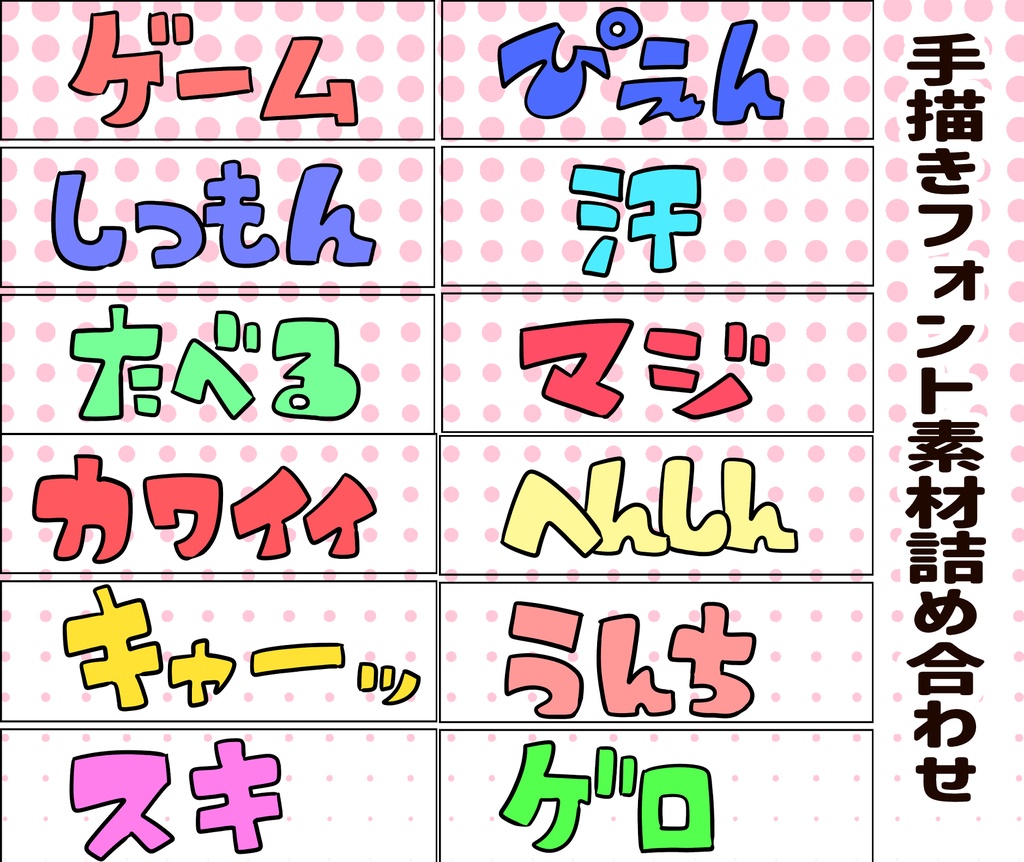
akiramoko手描きフォント・文字素材詰め合わせ・配信や配布物に応援パック(同じ内容です)Digital100 JPYAdd to CartBuy a GiftDownloadDigital0 JPYFree Download6.png (208 KB)Free Download3.png (307 KB)Free Download5.png (236 KB)Free Download1.png (253 KB)Free Download2.png (224 KB)Free Download4.png (270 KB)6.png3.png5.png1.png2.png4.pngAbout Gift柔らかな印象の手描きフォントです。 サムネイルや配布物、動画内素材 こちらは配信者向けのワードが多いかと思います。 様々な用途でお使いになれます。 色変更拡大縮小変形、ご自由にお使いください。 自作発言のみお止めください。 PNGデータ 600dpiakiramokoVisit FANBOX!Stickers騒がしい素直な猫のステッカーakiramoko770 JPYStickers素直な猫のステッカーakiramoko770 JPYT-Shirtsやるなら今しかねぇ猫akiramoko1,750 JPYAcrylic Keychains素直な猫のアクキーakiramoko880 JPYAcrylic Keychains騒がしい素直な猫akiramoko1,060 JPYIllustration (Other)歯科衛生士・イラスト詰め合わせakiramoko100 JPYFonts手描きフォント・文字素材詰め合わせ・配信や配布物にakiramoko100 JPYFonts手書きフォント・文字素材詰め合わせakiramoko100 JPYGlasses & Tumblers & Mugsクロネコマグakiramoko1,750 JPYAcrylic Keychainsクロネコチャンakiramoko880 JPYIllustration (Other)手書き文字・文字素材詰め合わせakiramoko100 JPYFonts手書きフォント・文字素材詰め合わせakiramoko100 JPYMaterials (Other)配信用素材・ビスケットakiramoko100 JPYMaterials (Other)配信素材・手描きフォントakiramoko100 JPYIllustration (Other)スケジュールメモ帳akiramoko0 JPYBackground Images背景画像・星空akiramoko0 JPYMaterials (Other)背景素材集akiramoko100 JPY~Photos【配信画面】写真立て12種・推し色akiramoko100 JPYIllustration (Other)歯科衛生士・歯科助手イラストakiramoko100 JPYGraphics【配信】花瓶・観葉植物セット【VTuber】akiramoko100 JPYSee More